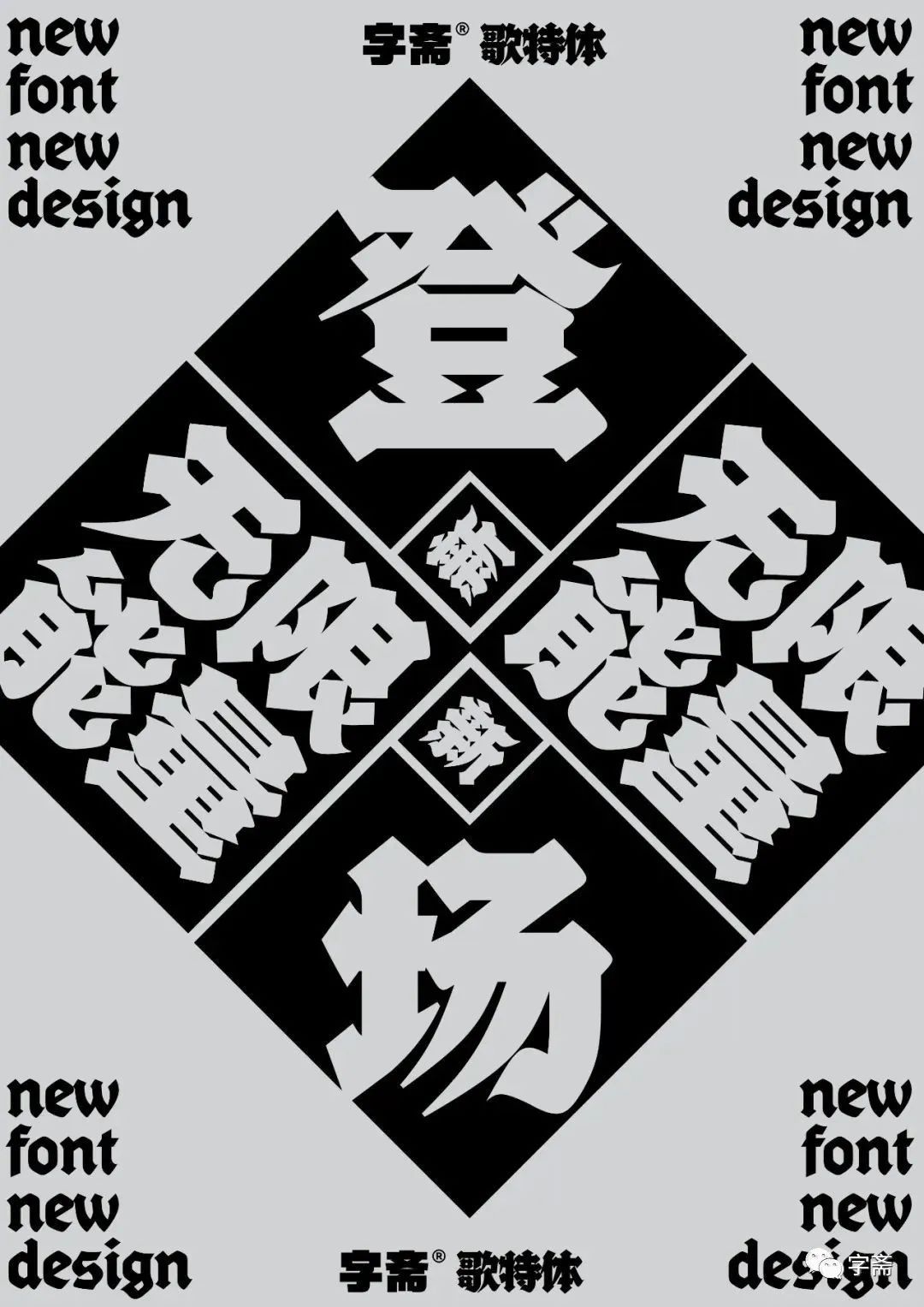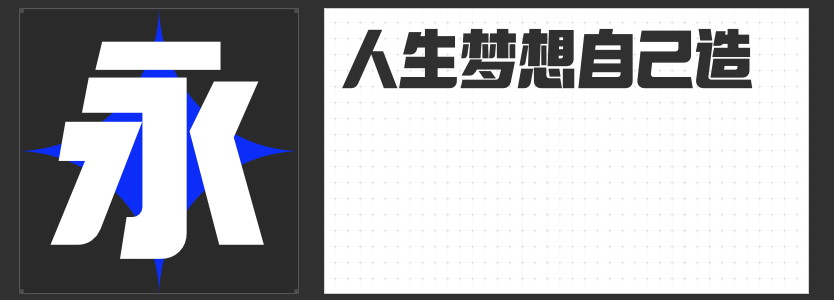
四款非常规字体助你渲染超燃气氛设计!
在设计的世界里,字体不仅是文字的载体,更是情感和创意的传达者。今天,我将为大家推荐四款各具特色的字体——“高手字斋哥特体Pro”、“励字暴风简 超级黑”、“造字侠伏魔简繁 传神”和“励字造梦简 超粗”。
这款字体以其独特的哥特式风格脱颖而出,笔画纤细而有力,线条流畅且充满张力。它适合用于各类高端设计,如时尚杂志封面、品牌标识和广告海报等。高手字斋哥特体Pro的优雅与力量并存,能够赋予设计作品以独特的视觉冲击力,使品牌信息更加引人注目。
这款字体以极简风格著称,笔画粗犷、对比强烈,给人以强烈的视觉震撼。励字暴风简 超级黑非常适合用于需要强调文字信息的设计场景,如电影海报、游戏标题和社交媒体广告等。其简洁有力的风格能够迅速吸引观众的注意力,并留下深刻印象。
这款字体结合了传统书法与现代设计的元素,笔画流畅、结构匀称,既有传统文化的韵味,又不失现代感。造字侠伏魔简繁 传神适合用于各类文化宣传、书籍封面和包装设计等。它能够传达出深厚的文化底蕴和审美价值,使设计作品更加传神和动人。
4.励字造梦简 超粗
这款字体以其超粗的笔画和独特的造型脱颖而出,极具视觉冲击力。励字造梦简 超粗适合用于需要强调力量感和厚重感的设计场景,如运动品牌广告、音乐节海报和电竞游戏宣传等。它能够赋予设计作品以强烈的个性和动感,使品牌信息更加鲜明和有力。
这四款字体各具特色,能够满足设计师在不同场景下的需求。无论是追求优雅与力量并存的高端设计,还是强调简洁有力的视觉冲击,或是传达传统文化韵味和现代感的设计作品,这些字体都能提供丰富的创意和灵感。选择适合的字体,让设计作品更加出色!